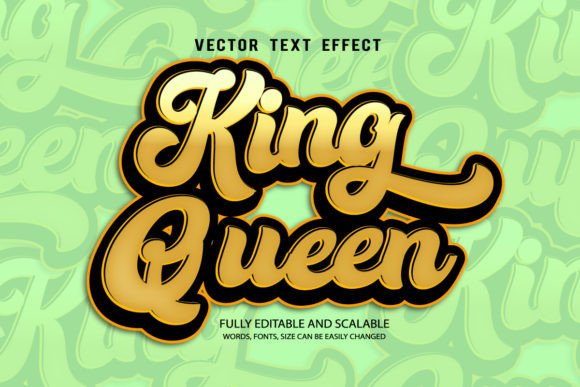
Modern Lettering Typography Font Style
Nếu bạn đang tìm kiếm các tài nguyên chất lượng cao như Modern Lettering Typography Font Style, gói cao cấp này là một lựa chọn tuyệt vời cho các dự án sáng tạo của bạn.
Được chế tác với độ chính xác cao, Modern Lettering Typography Font Style cung cấp các vector sạch, kiểu chữ mượt mà và giấy phép thương mại để bạn yên tâm.